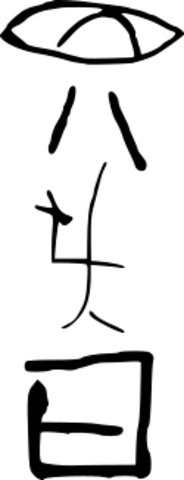
Historia de la tipografía
Primeras escrituras pictográficas
Marcas similares a la escritura dibujadas sobre caparazones de tortuga, descubiertos en la moderna Jiahu (China), datados hacia el 6000 a. C..